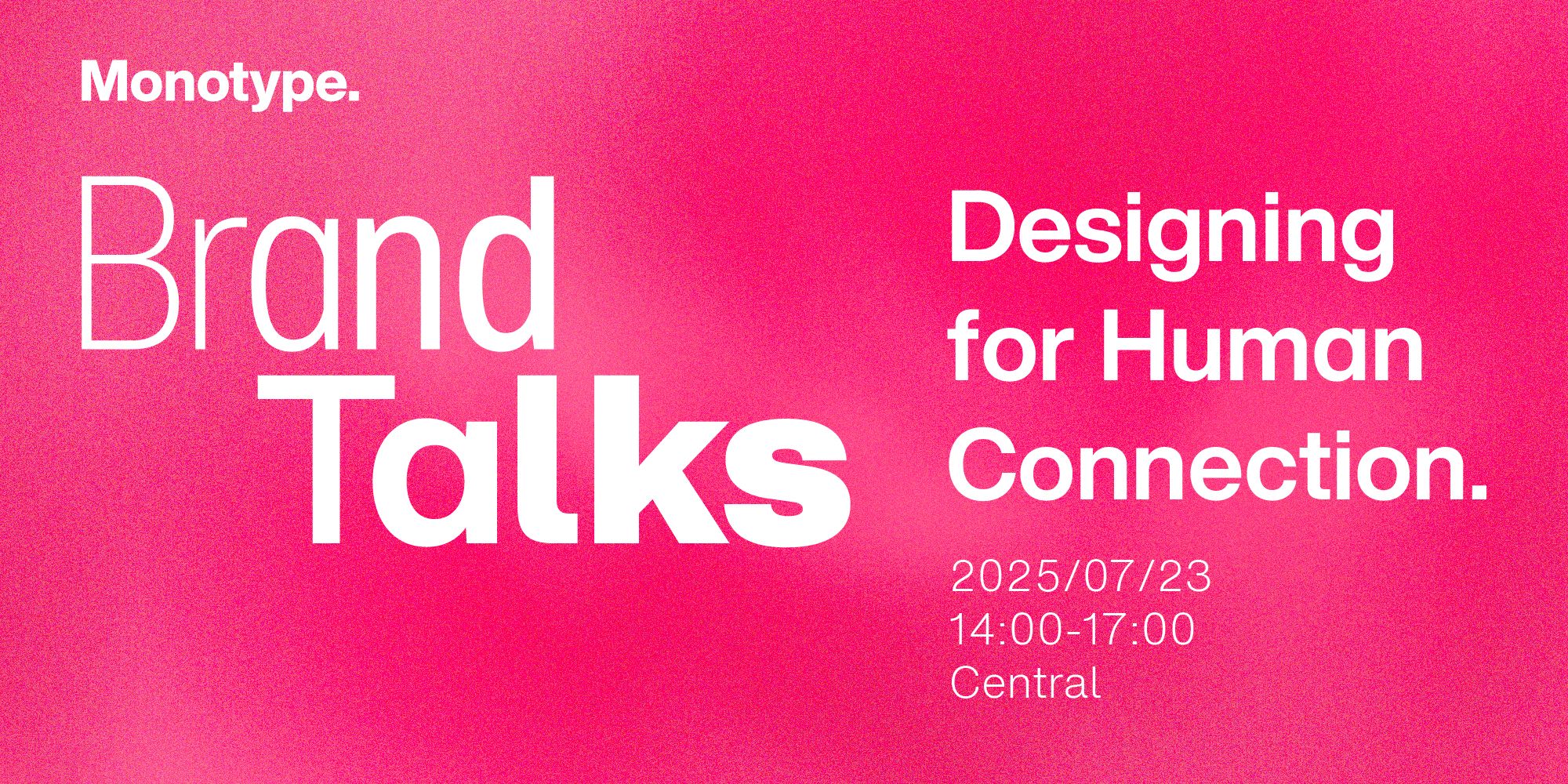
Brand Talks.
Monotype’s Global Brand Talks series is launching its Asia tour this July, with stops in Hong Kong, Shenzhen, Taipei, and Seoul. This event brings together leading designers, marketers, and branding professionals from around the world to explore the latest trends, share practical strategies, and spark new inspiration to help your brand succeed.
蒙納全球系列 Brand Talks 將於七月展開亞洲巡迴,包含香港、深圳、台北與首爾。本活動匯聚來自世界各地的設計、行銷與品牌專業人士,一同探討最新趨勢、分享實用策略,並激發靈感,助力品牌邁向成功。
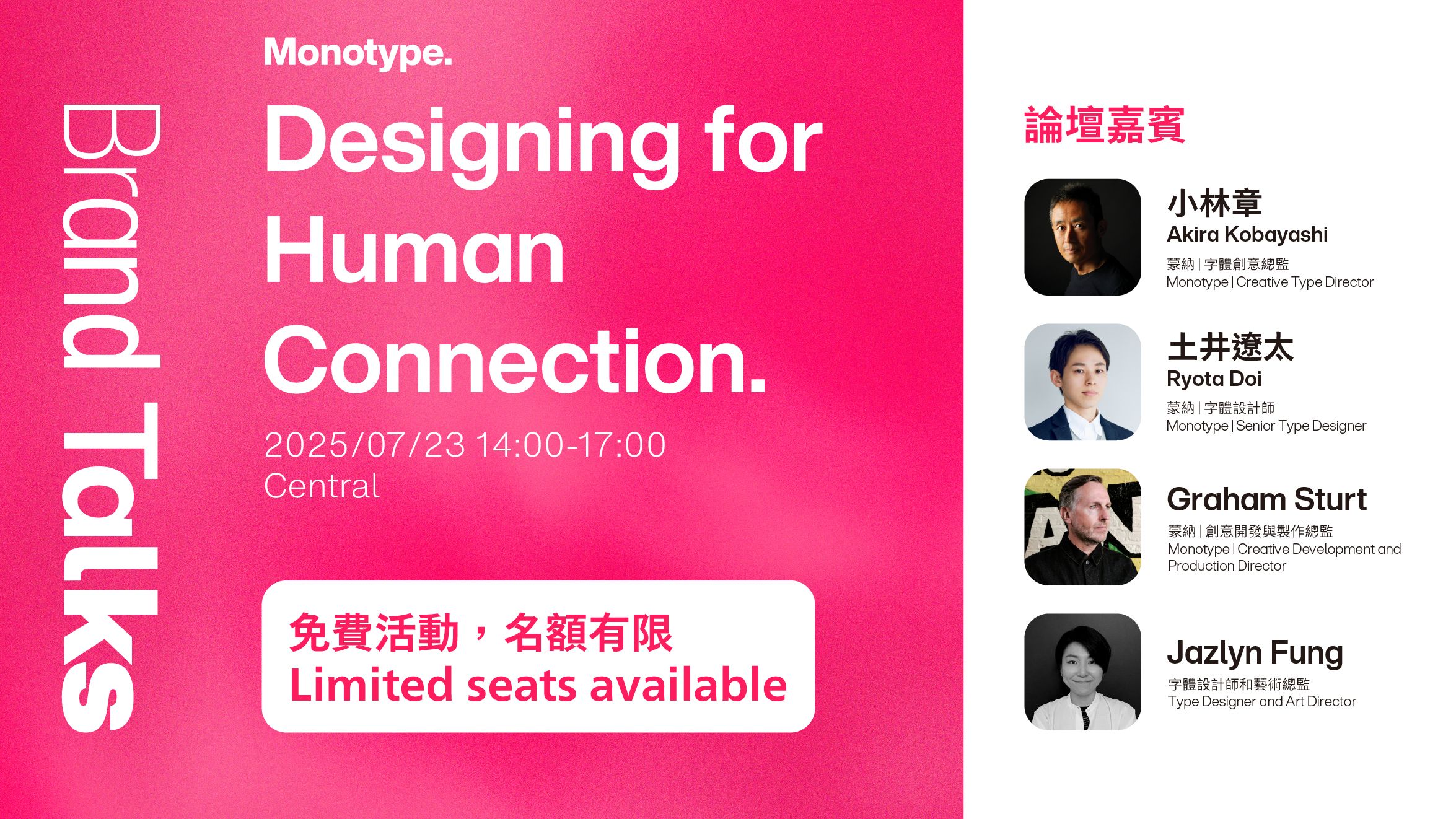
Theme 主題.
Designing for Human Connection.
AI and technology can enhance design efficiency and enable more personalized experiences, but only genuine human insight and emotional understanding can truly move people.
Monotype Brand Talks Hong Kong presents “Designing for Human Connection”—a deep exploration of how typography connects people, brands, and the city.
AI 與科技可以提升設計效率、個人化體驗,但唯有人性洞察與情感把握,才能讓產品、服務與體驗真正觸動人心、贏得用戶認同。Brand Talks Hong Kong 今年以「Designing for Human Connection」為主題,邀請國際頂尖字體設計師與創意領袖,探索字體如何串連人、品牌與城市。
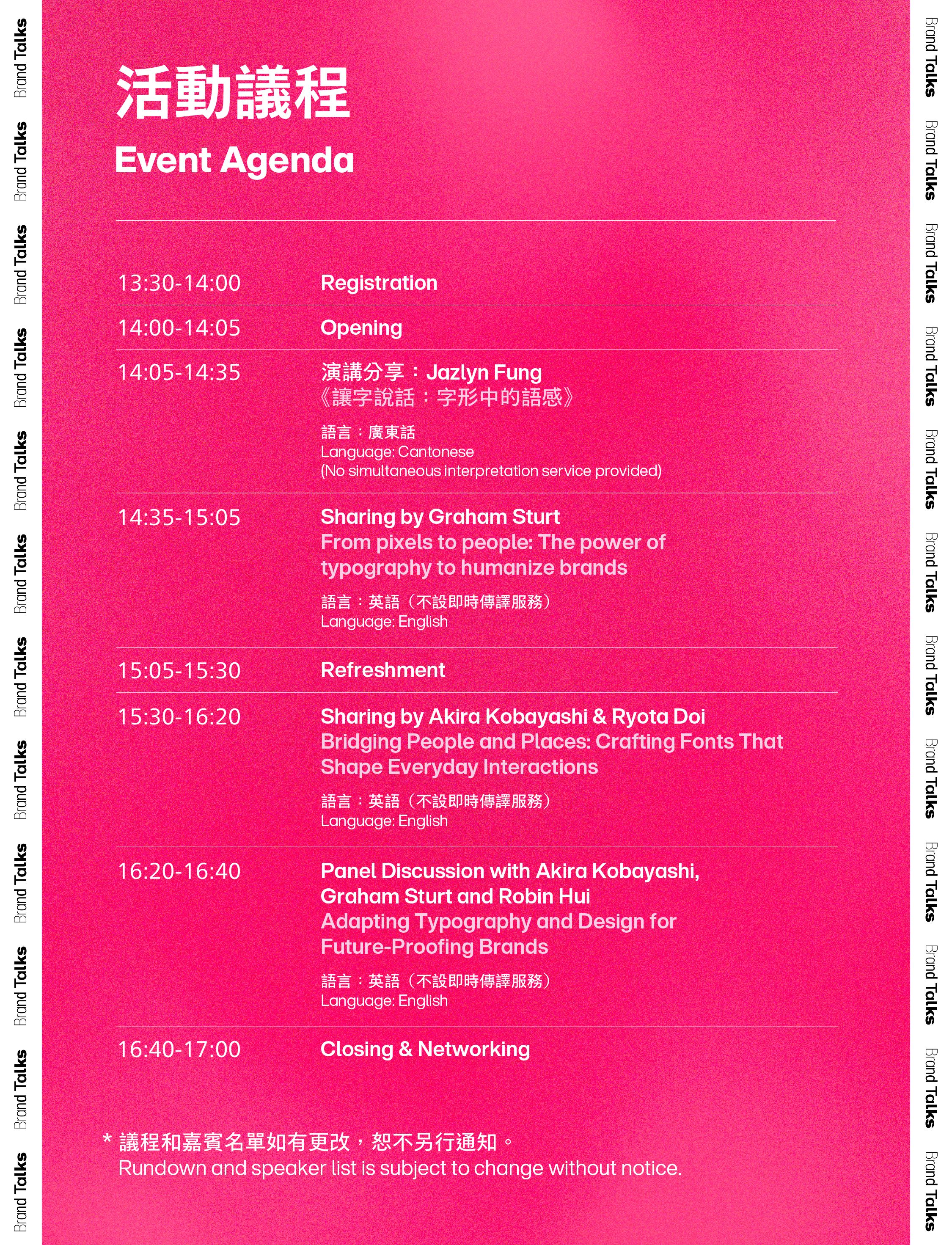
嘉賓簡介 Speaker Profile.
| 講者 | 簡介 |
小林章 | Akira Kobayashi has over 30 years of experience in type design and is recognized as one of the world’s leading Latin type designers. In 2022, he was awarded the TDC Medal and is often hailed as a foremost authority in the field. Kobayashi has collaborated with renowned designers such as Hermann Zapf and Adrian Frutiger on iconic typefaces like Optima Nova and Frutiger, and has created more than 50 typefaces, including Avenir Next and DIN Next. 小林章擁有三十多年字體設計經驗,是世界知名歐文字體設計師,2022年獲TDC獎章,被譽為「歐文字體第一人」。他曾於與 Hermann Zapf、Adrian Frutiger 合作,參與 Optima Nova、Frutiger 等經典字體設計,並創作超過五十款字體,包括 Avenir Next、DIN Next。 |
土井遼太 | Co-designer of Tazugane Gothic, Ryota Doi specializes in integrating Japanese and Latin type design. He contributed to the interior display typeface for JR Central’s N700S trains and is dedicated to advancing the internationalization and versatility of type design. Tazugane Gothic 設計者之一,專精於日文與歐文字體的融合設計。曾參與設計 JR 東海新型車輛 N700S 的車內顯示字體,致力於推動字體設計的國際化與多元應用。 |
Graham Sturt | Graham Sturt leads a diverse global in-house creative team. He has held creative leadership roles at internationally renowned agencies such as Interbrand and Superunion, delivering award-winning projects for brands including Heineken, WPP, ING, and PostNL. Graham’s work has been recognized by major international awards such as D&AD, Cannes Lions, and the European Design Awards, and he is known for driving innovation by integrating strategy with design. Graham Sturt 領導全球多元化的內部創意團隊。他曾於 Interbrand、Superunion 等國際知名機構擔任創意領導職務,為 Heineken、WPP、ING、PostNL 等品牌打造屢獲殊榮的專案。Graham 的作品獲得 D&AD、Cannes Lions、European Design Awards 等國際大獎肯定,並以結合策略與設計推動創新。 |
許大鵬 | Robin Hui joined Monotype Hong Kong as a type designer in 1988. He has been involved in a large number of type design and development projects, including the famous Monotype Hei, Sung and Kai families. Robin’s own creations include M Ngai, M Windy, M Comic, M Razor, and M Lady, to name a few. Custom type projects include work Nike 365SC & TC Chinese custom fonts - Robin won the Wood Pencil in the D&AD Awards 2022 for his work with Nike. 許大鵬於 1988 年加入蒙納香港公司,擔任字體設計師。 他參與了許多字體的設計和開發項目,包括著名的蒙納黑體、宋體和楷體家族。 Robin 自己的創作包括 M Ngai、M Windy、M Comic、M Razor 和 M Lady 等;定製字體項目包括 Nike 365SC 和 TC 中文定製字體作品 。Robin 憑藉與 Nike 合作的作品榮獲 2022 年 D&AD 大獎木鉛筆獎。 |
Jazlyn Fung | Jazlyn Fung is a Melbourne-based designer with a passion for typography. Originally from Hong Kong, she spent years working in environmental graphics and branding before moving to Melbourne, where she began focusing on type design and experimentation. Jazlyn’s work often draws from personal stories and experiences, resulting in typefaces that are playful, expressive, and full of character. Jazlyn Fung 是一位來自香港、現居墨爾本的設計師,多年於兩地從事品牌設計、環境平面設計及藝術展覽中的字體應用與創作。她從行業領域中對字體產生熱愛,現時專注於字體創作與實驗,以探索文字作為表達與溝通的視覺語言。 |